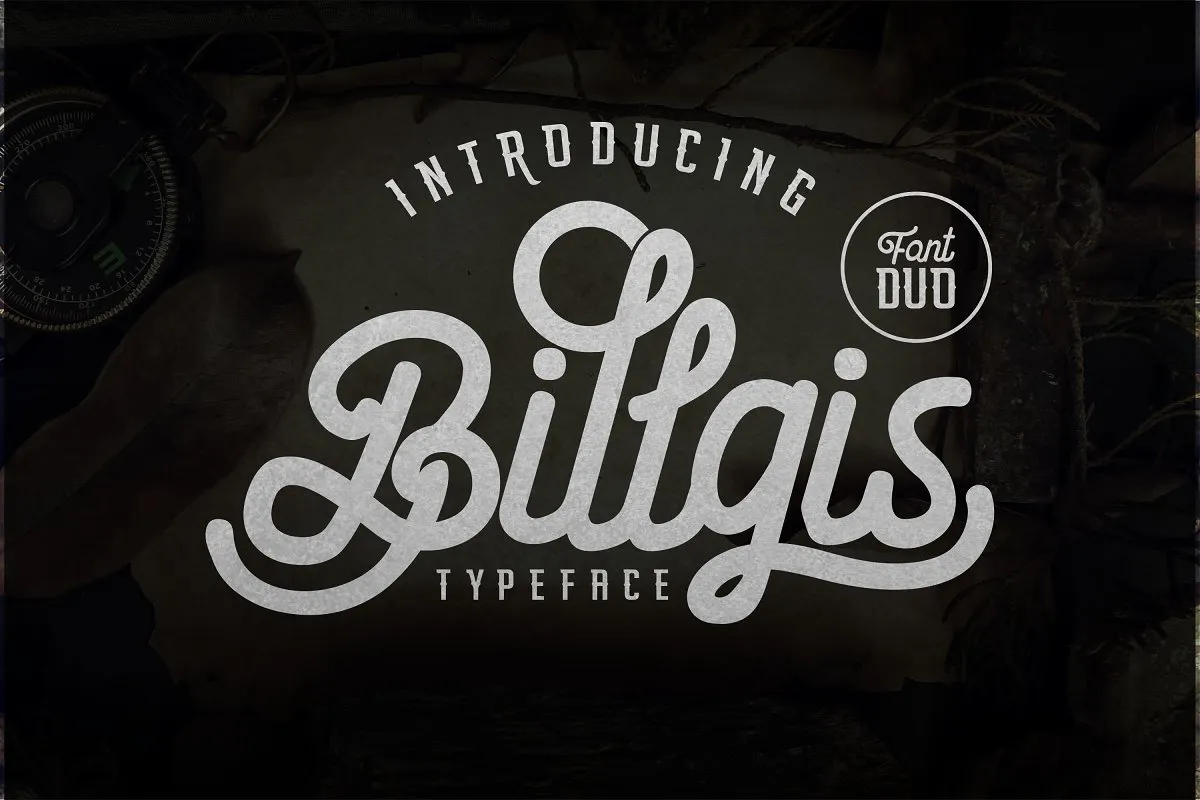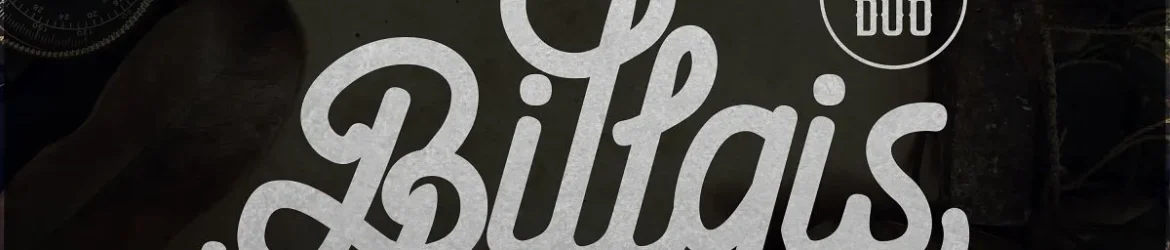
Bem-vindo a mais uma adição incrível para sua coleção de tipos de fontes! Hoje, apresentamos Billgis Font Duo. Esta exuberante dupla oferece um estilo de escrita manuscrita que irá dar ao seu projeto uma sensação natural e autêntica. Billgis é ideal para uma variedade de aplicativos, como fotografia, logotipos e marcação, convites, material de estação, designs de casamento, posts nas redes sociais, anúncios, embalagens de produtos, design de produto, rótulos, até mesmo marcas especiais ou outros eventos. Perfeito para aqueles que desejam dar um toque pessoal e natural a seus projetos, Billgis é uma fonte perfeita tanto se você está criando um logotipo exclusivo para sua marca, quanto se deseja personalizar o design de uma embalagem de produto ou até mesmo criar um rótulo único. Não importa qual projeto esteja trabalhando em mãos, a Billgis Font Duo trará uma qualidade especial que tornará seu trabalho ainda mais único e autêntico.